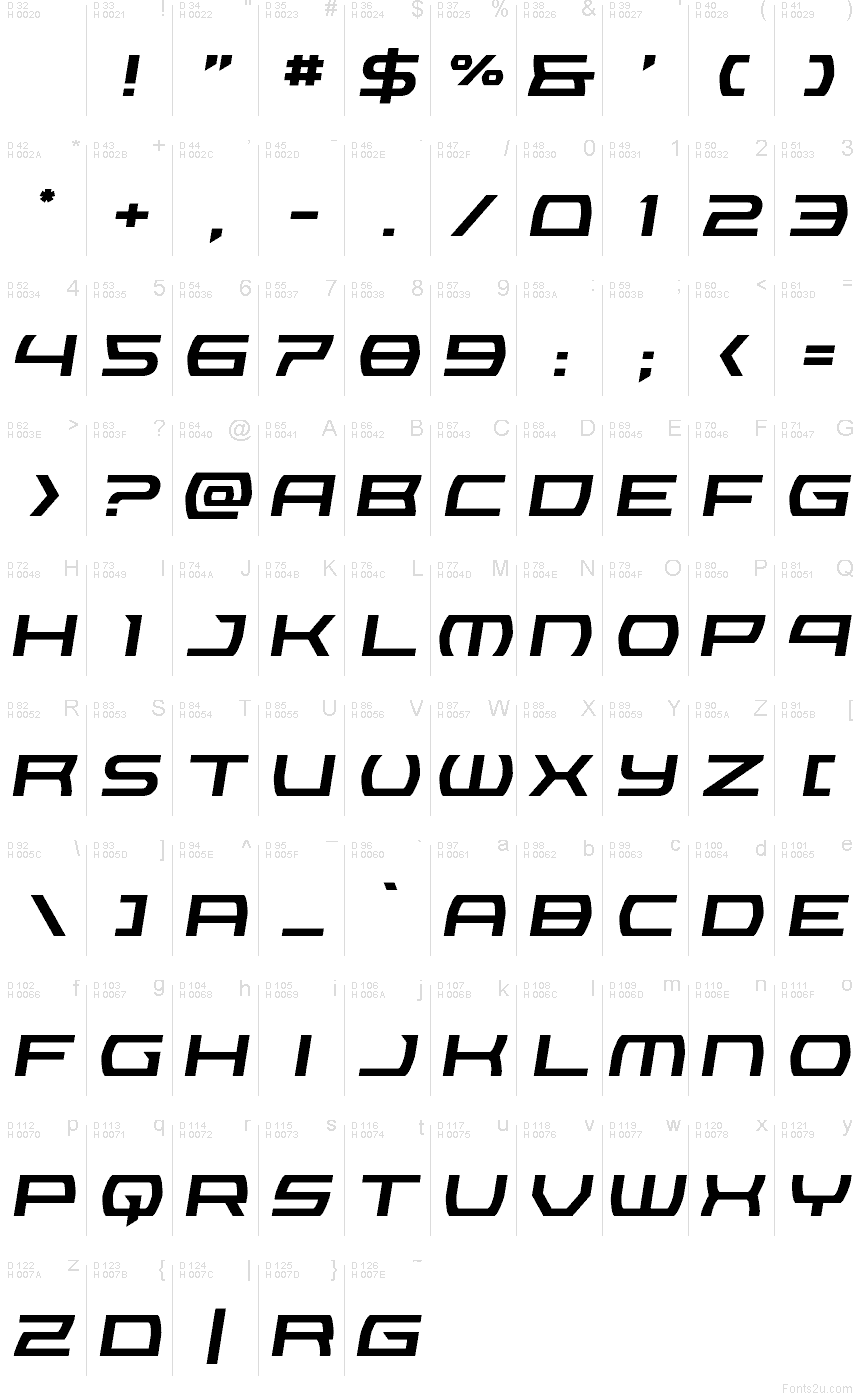
Icemaster Expanded Semi-Italic von Iconian Fonts ist eine kostenlose, futuristische Display-Schrift, die mit kühler, technischer Präzision besticht. Die Buchstaben sind breit und nach vorne geneigt, mit kantigen Kurven und sanften inneren Ausschnitten, die das Alphabet eher wie futuristische Sci-Fi-Beschilderung als wie eine gewöhnliche kursive Schrift wirken lassen.
Sie passt perfekt in Game-Logos, Tech-Poster, Album-Cover, Streaming-Titelgrafiken und Sport-Branding, wo eine kostenlose Schrift Schnelligkeit braucht, ohne überladen zu wirken. Verwenden Sie sie für kurze Überschriften, Monogramme und Slogans – die breiten Versalien und die stromlinienförmige Neigung verleihen selbst wenigen Buchstaben eine Dynamik von Eis und maschineller Perfektion.